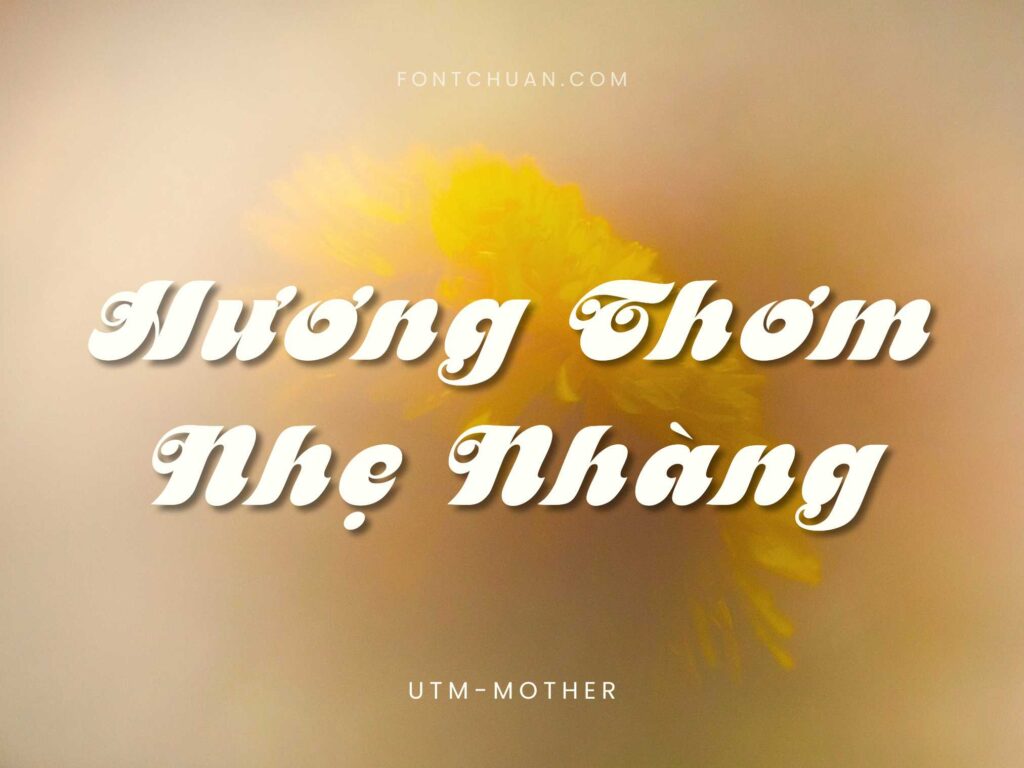
Font UTM Mother Việt Hóa
UTM Mother là một font chữ mang phong cách thư pháp hiện đại, kết hợp giữa sự mềm mại và thanh lịch, tạo cảm giác tinh tế và sang trọng trong thiết kế. Font này có thể được ứng dụng trong nhiều lĩnh vực từ in ấn đến thiết kế đồ họa. Font đã được Việt hóa bởi Thiên Minh, hỗ trợ đầy đủ tiếng Việt cùng hơn 200 ngôn ngữ khác, giúp mở rộng khả năng sử dụng. Thành viên của Font Chuẩn đã sưu tầm và giới thiệu font này nhằm đáp ứng nhu cầu bạn đọc, cung cấp nguồn tham khảo chất lượng và ứng dụng thực tế vào các dự án thiết kế
Về đặc điểm thiết kế, UTM Mother có các đường nét mềm mại, độ cong uyển chuyển và mang hơi hướng thư pháp hiện đại. Font này phù hợp với nhiều ứng dụng như thiết kế logo, thiệp mời, biển hiệu, tiêu đề trang web và các ấn phẩm sáng tạo. Các ngành nghề như quảng cáo, ẩm thực, thiệp cưới và giáo dục có thể tận dụng font này để tạo điểm nhấn và mang đến sự thanh lịch trong các sản phẩm thiết kế